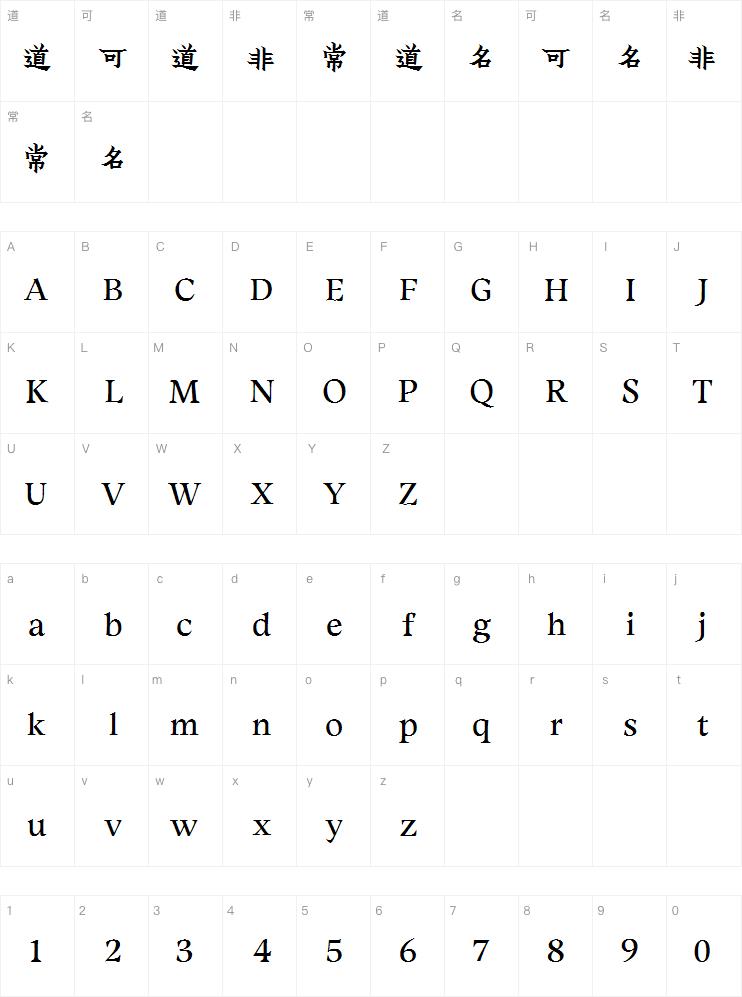
本字体吸收原字形“弃圆转、弃流畅、重方折、重金石”的特点,并加以几何化处理,在横收笔和横折等处设计了宋体折角,长横重而有力,起笔粗重翘头而行笔渐收,点画如斜风吹雨,溅落为长水滴形,与微倾的横画一起拖动整体字势沉向右下。横竖起笔有锐利、横向切入的起笔,矢量化后的曲线更加柔和雅致,进而拥有更广泛的应用场景。整字结构上为左侧横起笔和拖长的撇余留更多空间,左舒展右紧凑,结合笔画分布形成错落不规则的字形轮廓。